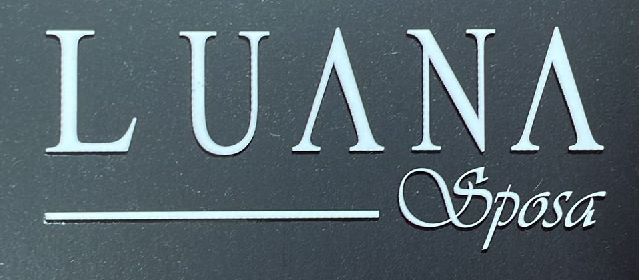
Bu font nedir bilen var mı? R10+++++
Trajan grubuna benzettim ama o değil. Bu fontu bilen var mıdır acaba?
Bu çıktı sonuç olarak ama ne kadar doğru bilemedim
Luana trajan a benziyor ama a harfinin içi koparılmış. Sağ alttaki de vivaldi olsa gerek
hocam bende ilk ona benzettimde değil maalesef ama alttaki nokta atışı teşekkür ederim
elle çizeceğim bulamadım maalesef